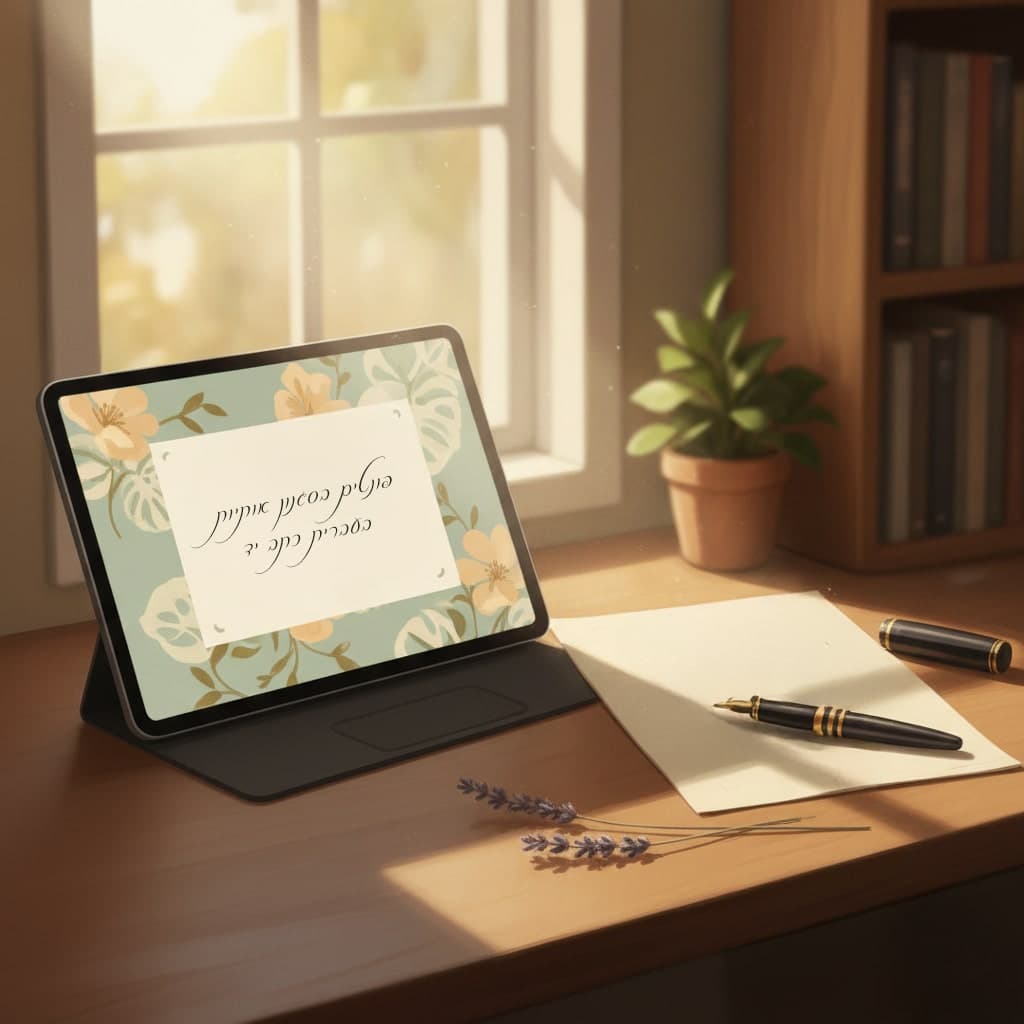
בעידן הדיגיטלי, פונטים בסגנון כתב יד הפכו לטרנד בולט ולבחירה מועדפת בקרב מעצבים. הם שוברים את התחושה הקרירה והממוחשבת של טקסטים דיגיטליים ומוסיפים אלמנט אנושי וחמים לכל עיצוב.
באמצעותם ניתן לשדר רוך, אינטימיות ויצירתיות, וליצור תחושת קרבה בין המילים לקורא. פונטים אלה משתלבים היטב בעולמות של מיתוג, כרזות, הזמנות ואפילו עיצוב אתרי אינטרנט.
הקסם שבכתב היד טמון בכך שהוא מצליח להעביר אישיות, סיפור ורגש דרך הצורה של כל אות ואות. בחירה נכונה של פונט יכולה להפוך טקסט רגיל למסר חי ונושם שמספר את הסיפור של המותג או הפרויקט.
במאמר זה נבחן את היתרונות הייחודיים של פונטים בסגנון כתב יד, נעמיק בסגנונות השונים של אותיות כתב יד בעברית, ונציע כלים וטיפים לשימוש מושכל ומאוזן בעיצוב טקסטים שמרגשים, מדברים בשפה אישית ומחברים את הקורא ברמה הרגשית.
פונטים בעברית עם אותיות בעברית כתב יד מציעים גיוון ועושר עיצובי יוצאי דופן, ההופכים אותם לבחירה מבוקשת בקרב מעצבים, בעלי עסקים ויוצרים.
הם מתאימים למגוון רחב של שימושים: החל מעיצוב של כרזות צבעוניות ומזמינות, דרך הזמנות לאירועים, ועד ליצירת לוגואים ממותגים וכרטיסי ביקור מעוררי עניין.
הפונטים הללו מדמים את תנועת היד האנושית ולכן משדרים חמימות, רכות ואותנטיות שקשה להשיג באמצעים אחרים.
שימוש נכון עם פונט כתב יד מעניק לעיצוב נופך אישי וייחודי, כזה שמרגיש קרוב ובלתי מתוכנת. מעבר לאסתטיקה, פונטים מסוג זה יוצרים תקשורת רגשית עם הקהל, מחזקים את זהות המותג ומבדילים אותו מהנוף הדיגיטלי האחיד שמקיף אותנו.
בנוסף, הם שוברים את הנוקשות של עיצובים ממוחשבים ומכניסים אלמנט של רגש וחום אנושי.
יש בהם משהו אישי, כאילו נכתב במיוחד עבור הצופה, שמחזק את תחושת הקשר והאותנטיות. הפונט “מדבר” בגובה העיניים ומזמין להקשיב.
כל פונט מעניק לעיצוב גוון שונה. הגיוון מאפשר להתאים כל מסר לקהל היעד בצורה מדויקת.
יש לשלב פונטים אותיות בעברית כתב יד בצורה מאוזנת עם פונטים אחרים. לדוגמה, ניתן להשתמש בפונט של כתב יד עבור הכותרות ופונט קריא יותר לטקסט הגוף.
השילוב בין שני הסגנונות יוצר עניין חזותי, מבליט את המסרים המרכזיים ומעניק לעיצוב תחושת מקצועיות.
בנוסף, שימוש מושכל בניגודיות בין הפונטים עוזר להדגיש היררכיה טקסטואלית ולכוון את עין הצופה באופן טבעי.
כשעובדים על עיצוב של כרזות, חשוב להקפיד על מרווחים נכונים בין הטקסטים כדי לשמור על קריאות. ריווח מאוזן מעניק לעיצוב אוויר לנשימה ומונע תחושת צפיפות שמקשה על הקורא.
גם בחירת גודל האות והמרחק מהאלמנטים הגרפיים משפיעים ישירות על חוויית הקריאה והאסתטיקה הכללית.
יש להימנע משימוש יתר בפונטים של אותיות בעברית כתב יד, כדי לא להעמיס על הצופה ולשמור על המראה הכללי של העיצוב. עודף אלמנטים טיפוגרפיים עלול לבלבל ולגרום לעייפות ויזואלית.
עדיף לבחור נקודות מפתח בעיצוב שבהן הפונט הייחודי יבלוט – כמו כותרת או משפט מפתח – ולתת לו את הבמה בלי ליצור עומס מיותר.
הם מתאימים במיוחד כאשר רוצים ליצור תחושת קרבה ואמינות, למשל בקמפיינים הפונים ישירות ללקוח או בעיצוב המבליט ערכים של משפחתיות ויצירתיות.
שילוב נכון של צבעים, קומפוזיציה ופונט בכתב יד מעניק לכרזה רושם אנושי וחם שמבדיל אותה מפרסומים גנריים וקרים.
הם מאפשרים לבעל העסק לבטא את האישיות שלו דרך עיצוב מינימליסטי אך מלא אופי, כזה שנשאר בזיכרון.
שימוש בפונט מסוג זה בכרטיס ביקור מעניק תחושת בוטיקיות ויחס אישי – אלמנט חשוב במיוחד במיתוג של בעלי מקצוע חופשיים, אמנים או מעצבים.
עיצוב טקסט בפונט שמדמה כתב יד יוצר תחושה טבעית ואמיתית, כאילו מישהו כתב במיוחד עבור הקורא. השימוש הזה מוסיף גיוון לפיד הדיגיטלי ומחזק את הקשר בין היוצר לעוקב, במיוחד כשמשלבים אותו עם צבעים חמים ותמונות אותנטיות.
לסיכום, פונטים בסגנון כתב יד הם כלי עיצובי רב עוצמה, המאפשר ליצור חיבור משמעותי עם הקהל.
אל תהססו לשלב את פונטים כתב יד בעיצובים שלכם ולהביא את האישיות שלכם לידי ביטוי.
בחירה נכונה תלויה במסר ובאופי העיצוב. אם רוצים לשדר קלילות כדאי לבחור פונט מעוגל וזורם, ואם רוצים תחושת יוקרה עדיף סגנון מוקפד ואלגנטי. חשוב לבדוק שהפונט נשאר קריא גם בגודל קטן.
הדרך הנכונה היא לשמור על איזון: להשתמש בפונט כתב יד לכותרות, ובפונט פשוט וקריא לטקסטים ארוכים. השילוב הזה שומר על היררכיה ברורה ותחושת סדר בעיצוב.